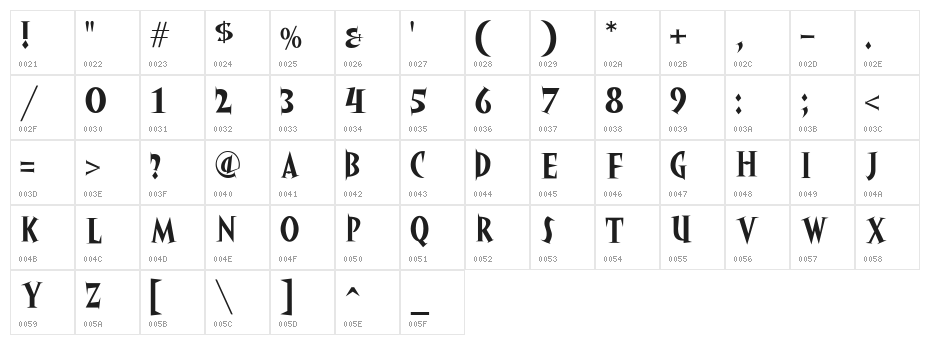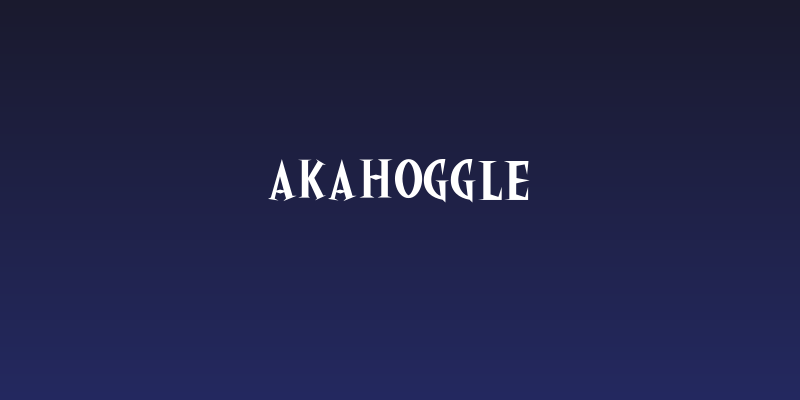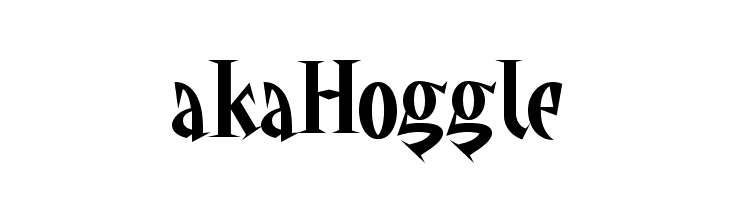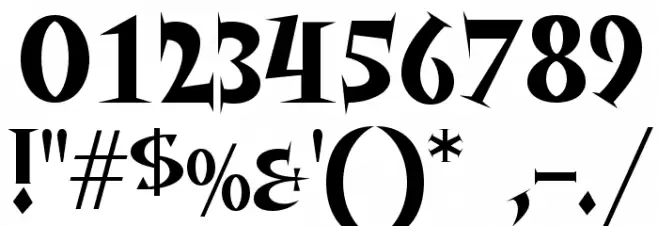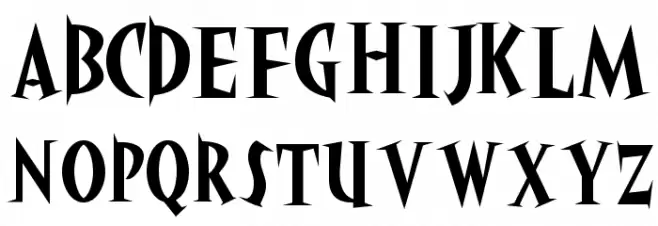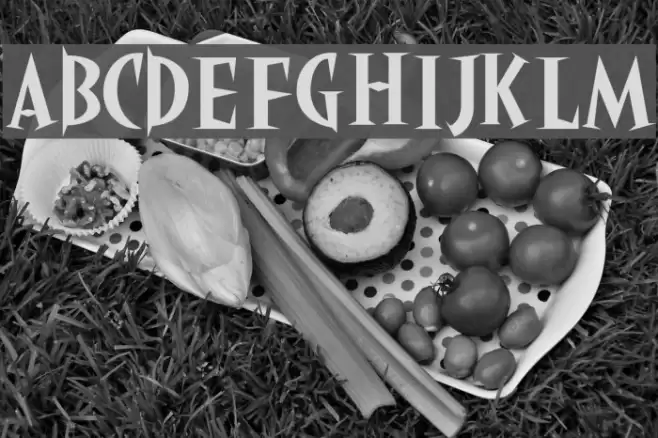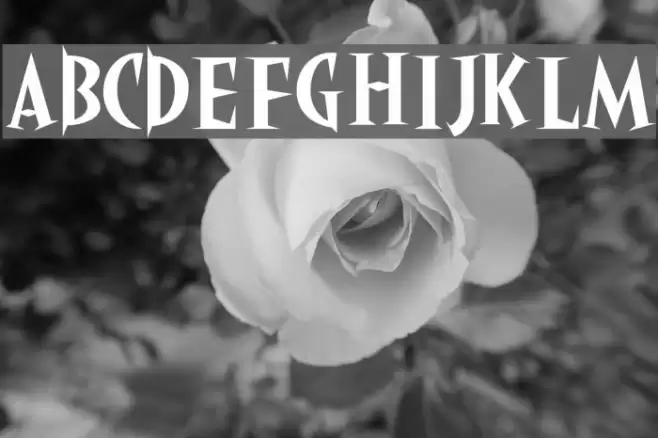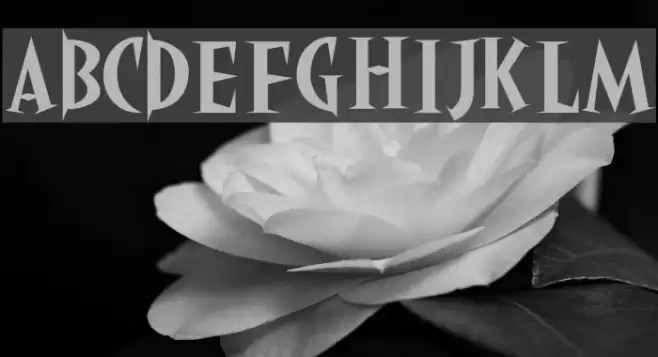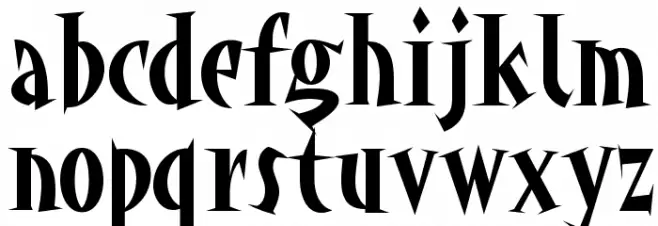
akaHoggle Font
| Estilo geral | Gothic, Modern |
| Projetos propostos | Ideal for branding, posters, book covers, and any project requiring a dramatic and impactful typeface. |